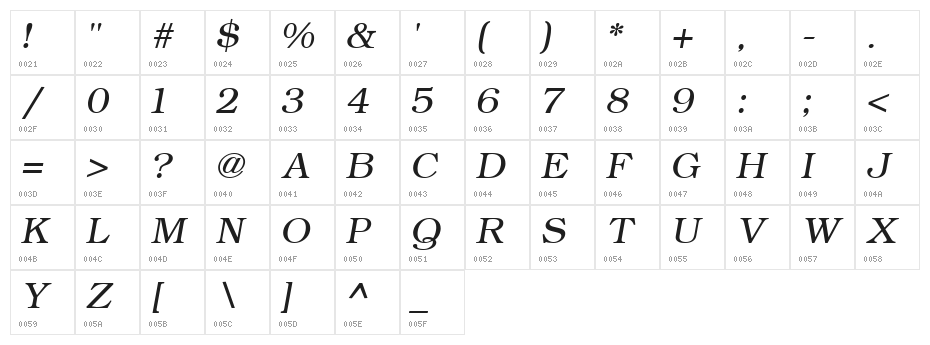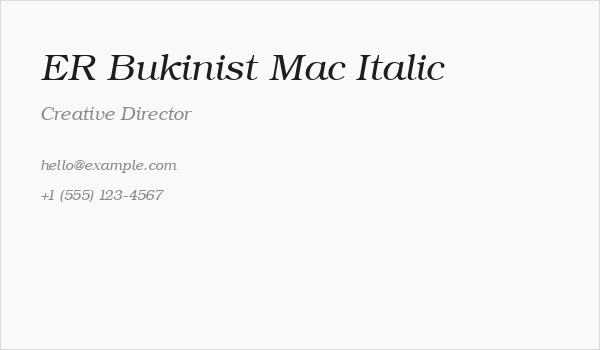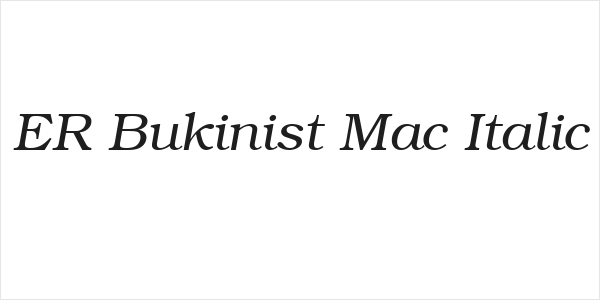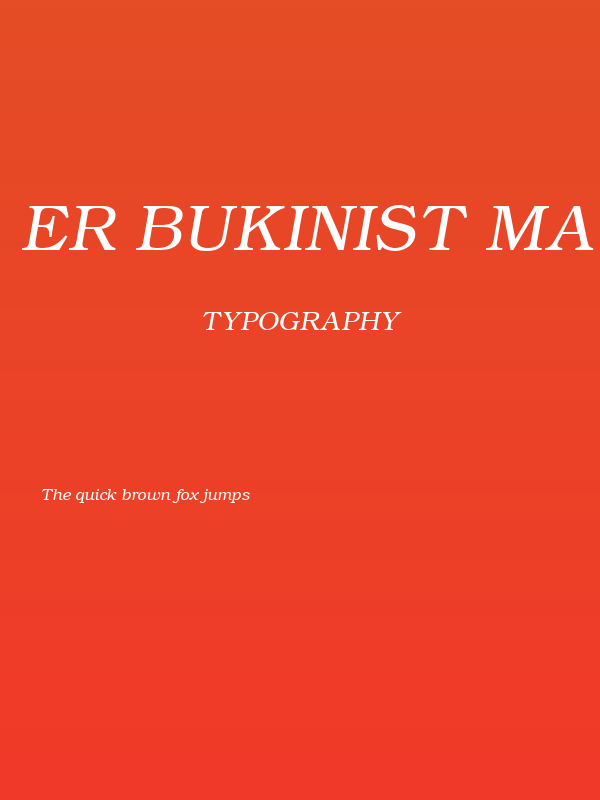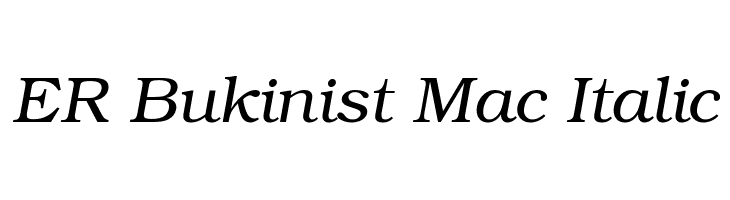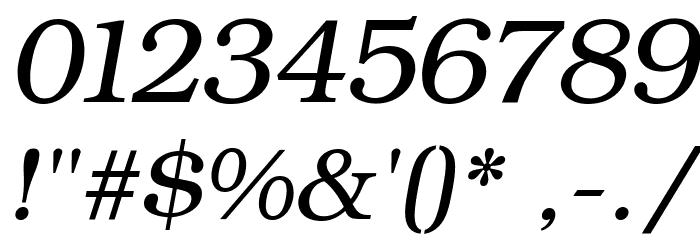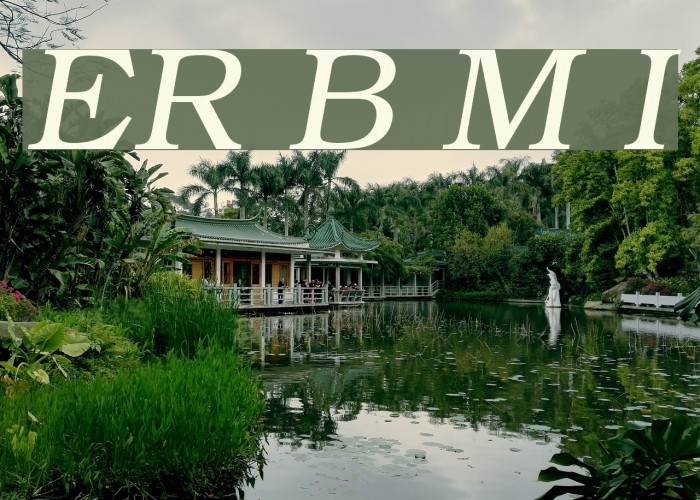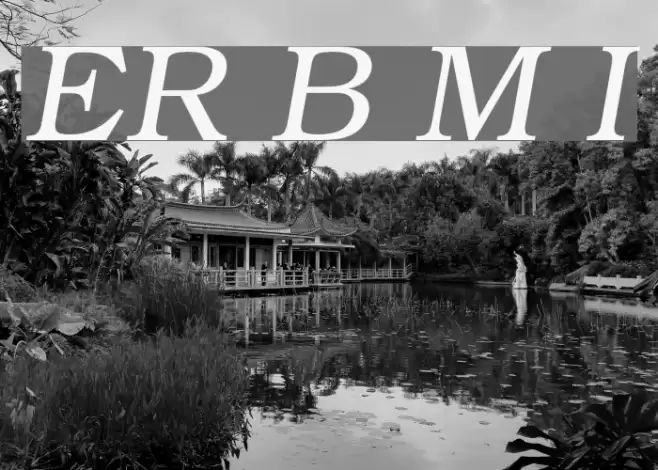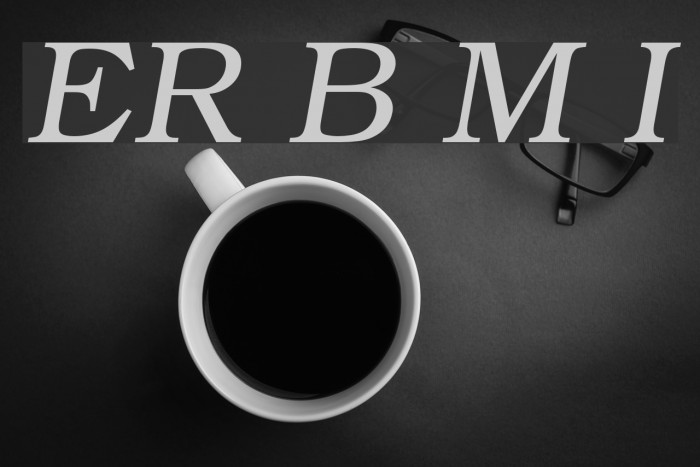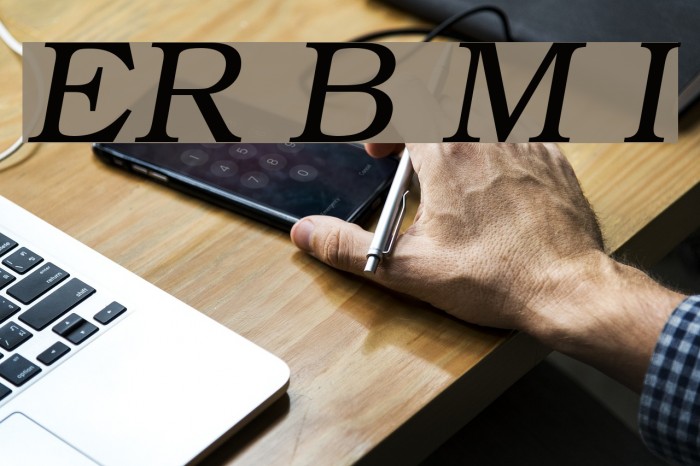
ER Bukinist Mac Italic Font
| Gesamtstil | Classic |
| Anwendungsfall | Headlines, Body text, Logos |
| Vorgeschlagene Projekte | Ideal for editorial design, book covers, formal invitations, and branding that requires a touch of elegance and tradition. |